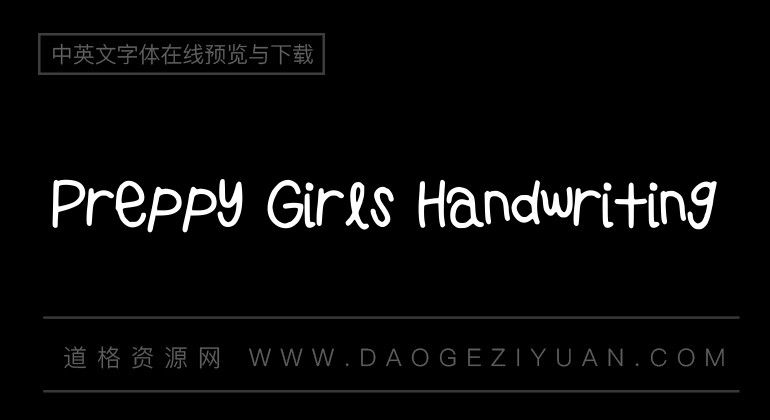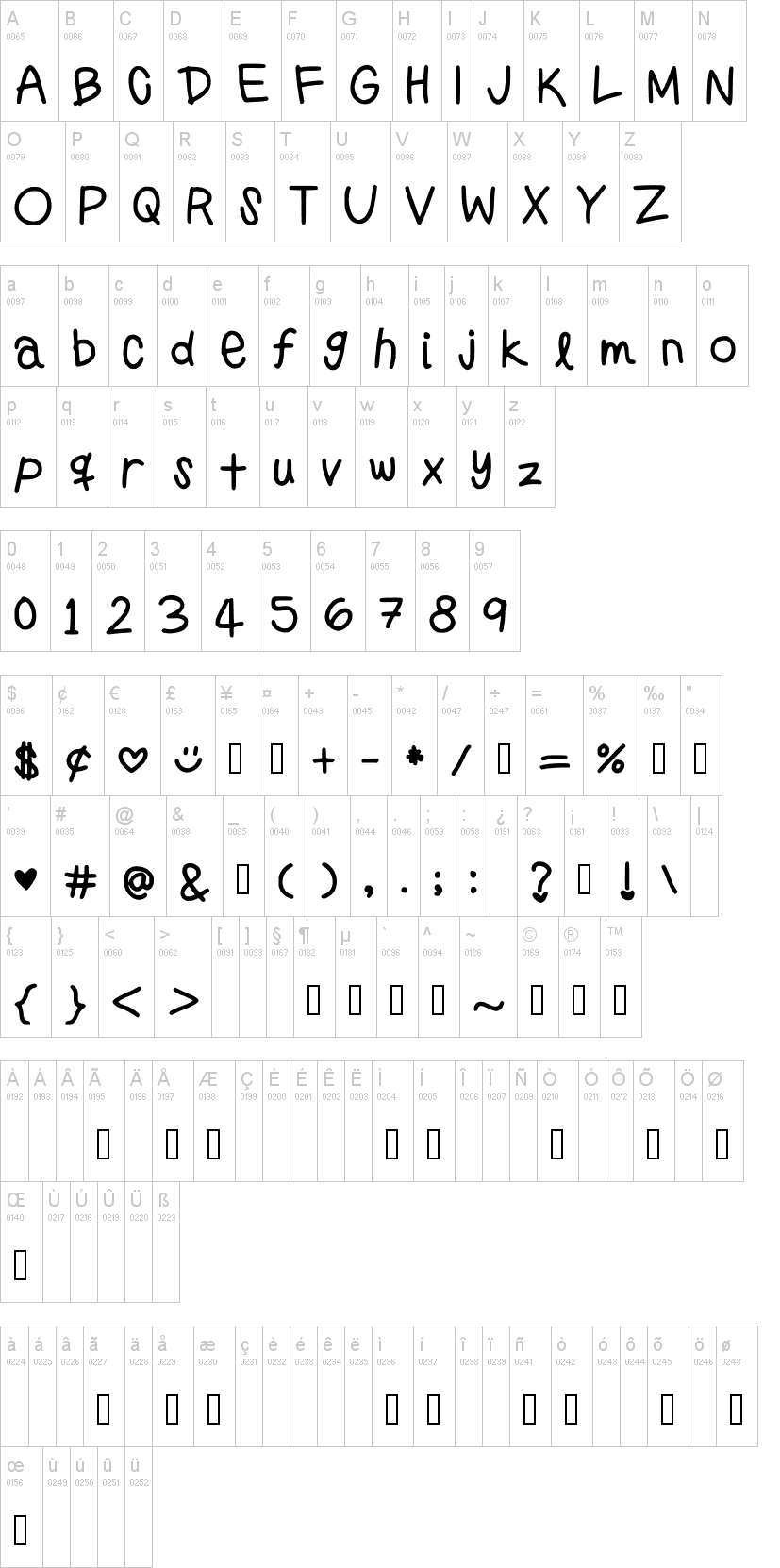
Preppy Girls Handwriting 字体是一种非常漂亮、清新、优雅的手写字体,适合用于女性相关的设计作品,如品牌标识、海报、招贴、包装、贺卡、书籍封面等。 这个字体基于女性手写字体的风格,使用了优美的笔画、细腻的线条和优雅的排版,让字体看起来非常舒适和自然。此外,字体还包含了多种替代字符和连字,可以让你创造出更加丰富和独特的设计效果。 总的来说,Preppy Girls Handwriting 字体是一种非常适合用于女性品牌和设计作品的优美手写字体,可以为设计带来更加清新、自然和优雅的感觉。内容介绍
Preppy Girls Handwriting是一款非常不错的手写艺术字体,具有很好的视觉感,适合于文化类的宣传设计、商业类品牌的广告和产品包装设计以及个性化文字排版等较多场景。